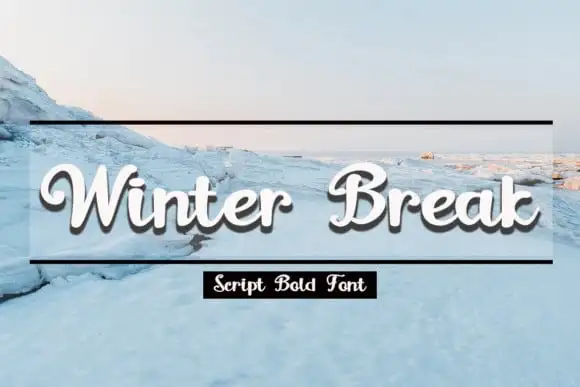
Winter Break Calligraphy Font
A fonte ‘Winter Break Calligraphy Font’ é perfeita para aqueles que buscam uma escrita script elegante e única para seus projetos criativos. Desenvolvida pelo designer Supersemar Letter, essa fonte está repleta de frescor e fluidez, com cada letra parecendo ser um registro cuidadoso da mão do artesão. Ideal para diversas aplicações, desde cartões de agradecimento, cartões de convidado, convites casamento e até mesmo logos e cards empresariais, essa fonte traz uma pitada de personalidade e romantismo. Ela encaixa-se perfeitamente nas demandas modernas das criações digitais, dando um toque especial e personalizado aos designs mais tradicionais. Com a ‘Winter Break Calligraphy Font’, transforme seus projetos em algo que chama atenção e destaca o seu trabalho de design.